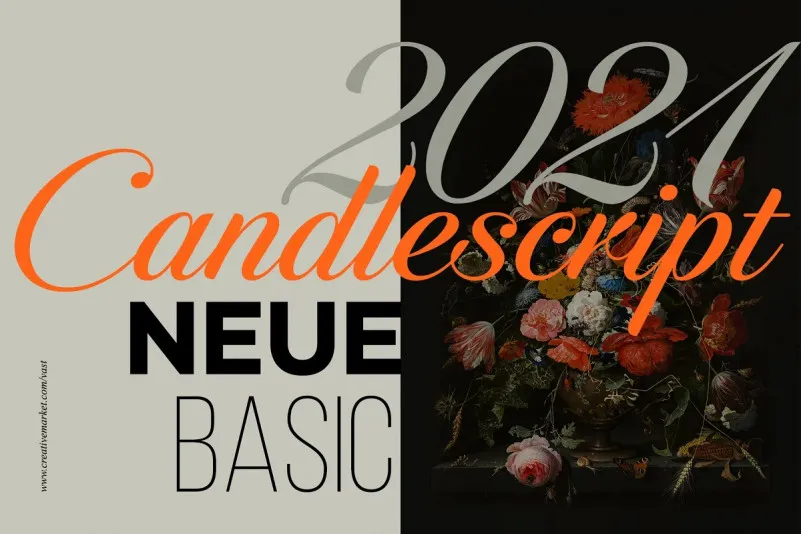
A ‘Candlescript Neue Font’ é uma nova fonte script que se destaca pela sua linha base suave e moderna, ao mesmo tempo feminina e trendy. Fundamentada no design de estilo clássico dos tachos de cobre com a incorporação de linhas modernas e extremamente precisas, esta fonte revela um toque naturalmente elegante e uma expressão fluida, perfeita tanto para exibição em monitores quanto impressão em diversos tamanhos. Inspirada no encanto da arte do tachos de cobre, mas revigorada para adaptar-se a uma era moderna, esta fonte traz um toque autêntico e sofisticado, perfeito tanto para aplicações digitais como impressões gráficas em dimensões variadas. Escolha a sua próxima fonte script com ‘Candlescript Neue Font’, quebrando as barreiras do tradicional para explorar o novo espaço da arte de escrita digital.